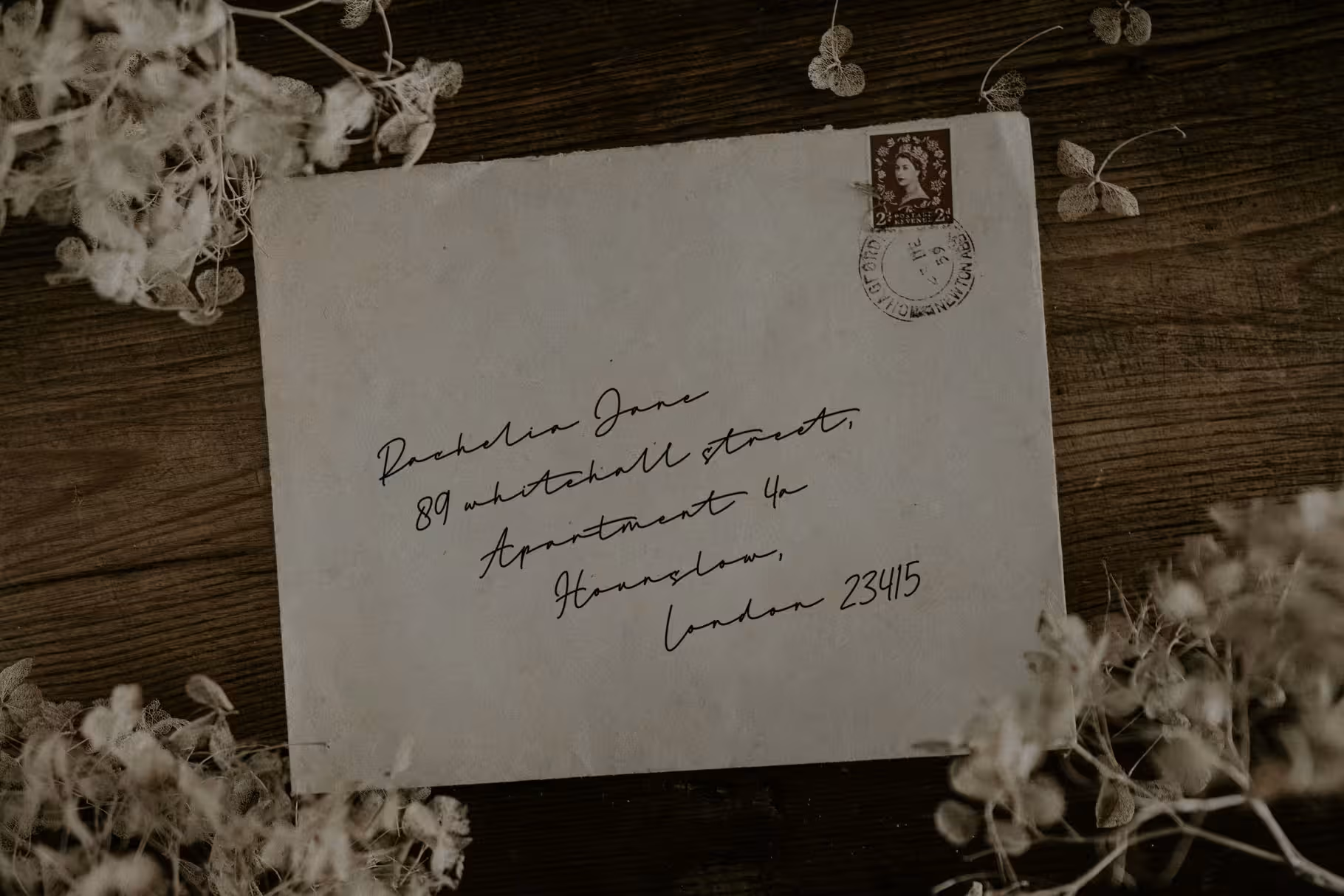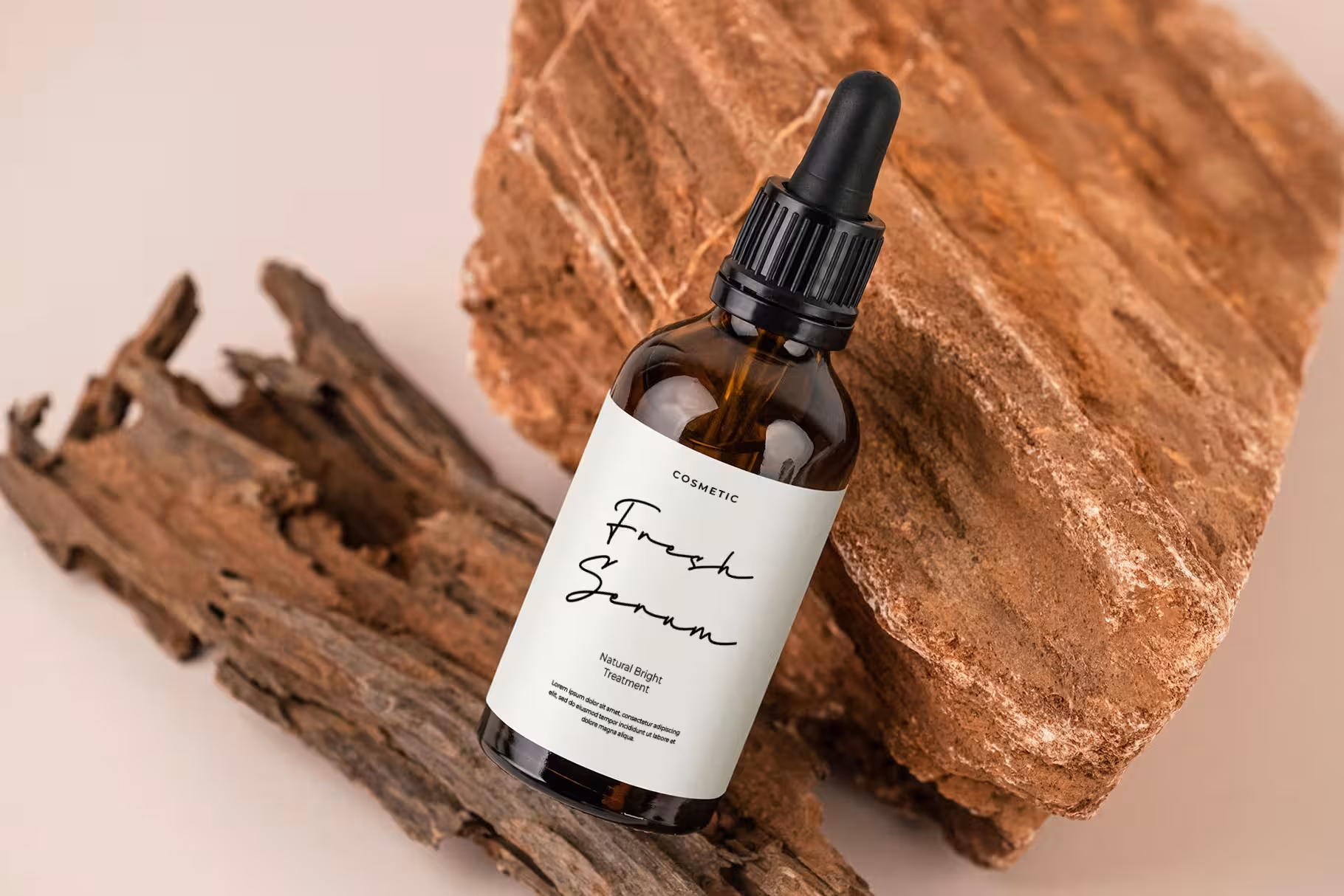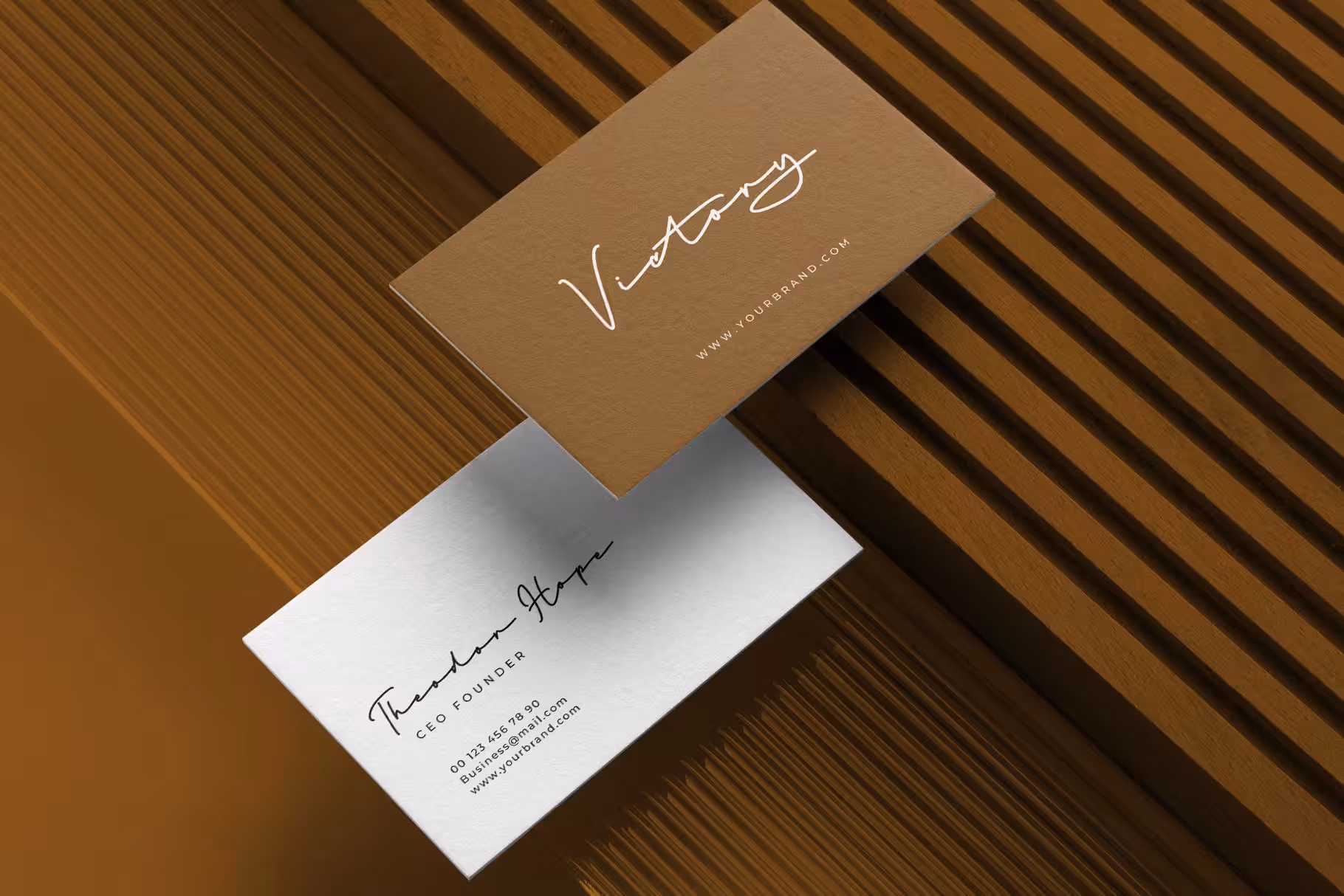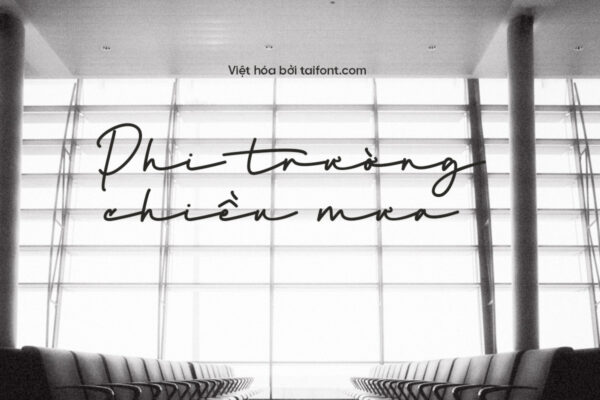
Giới thiệu về Font TF Ganttecy Việt hóa
TF Ganttecy Việt hóa là một font chữ viết tay (script font) nổi bật với vẻ đẹp tinh tế, duyên dáng và đầy quyến rũ, lý tưởng để tạo nên sự sang trọng và cá tính riêng cho các thiết kế. Font này mang đến cảm giác như những nét chữ được viết tay một cách mềm mại, uyển chuyển, toát lên sự nghệ thuật, lãng mạn và đẳng cấp.
Với sự duyên dáng trong từng đường nét và tính thẩm mỹ cao, Ganttecy là lựa chọn hoàn hảo cho các ấn phẩm cần sự sang trọng và khác biệt, đặc biệt là trong các lĩnh vực:
- Thiết kế thiệp: Hoàn hảo để sử dụng cho các thiệp mời sự kiện đặc biệt, thiệp cưới, thiệp sinh nhật hoặc các thiệp chúc mừng. Nét chữ viết tay thanh lịch của font sẽ biến những lời mời, lời chúc trở nên nghệ thuật, lãng mạn và đầy cảm hứng, tạo cảm giác cá nhân hóa và ấm áp, đồng thời truyền tải sự trang trọng.
- Thiết kế mỹ phẩm: Lý tưởng cho các nhãn hiệu mỹ phẩm muốn truyền tải sự sang trọng, tinh tế và một chút phong cách thủ công. Font này có thể dùng cho logo, bao bì sản phẩm, hoặc các chiến dịch quảng bá, đặc biệt là những sản phẩm nhấn mạnh tính nghệ thuật, sự tự nhiên và chất lượng cao.
- Thiết kế thời trang: Phù hợp cho các thương hiệu thời trang cao cấp, từ logo, nhãn mác sản phẩm, đến các chiến dịch quảng bá bộ sưu tập. Ganttecy giúp truyền tải vẻ đẹp thanh lịch, đẳng cấp và độc đáo, nâng tầm giá trị thương hiệu.
- Trích dẫn và slogan: Tuyệt vời để tạo các câu trích dẫn đầy cảm hứng, slogan hoặc các dòng chữ cần sự nổi bật và mang tính biểu cảm trên mạng xã hội hoặc các ấn phẩm khác, đặc biệt khi kết hợp với hình ảnh mang hơi hướng cổ điển hoặc nghệ thuật.
Với TF Ganttecy Việt hóa, bạn có thể dễ dàng thổi hồn nghệ thuật, sự tinh tế và vẻ đẹp lãng mạn vào các thiết kế, tạo ra những sản phẩm không chỉ đẹp mắt mà còn đầy cảm xúc và sức hút đặc biệt.